모노타입, AI 영상 편집 툴 ‘필모라’에 200개 폰트 담는다
경쟁이 치열한 콘텐츠 환경에서 타이포그래피는 핵심 차별화 요소
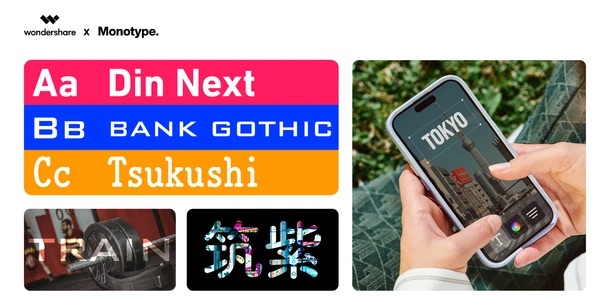
글로벌 폰트 및 서체 기술 기업 모노타입(Monotype)이 200종의 고품질 폰트를 원더쉐어(Wondershare)의 AI 기반 영상 편집 툴 ‘필모라(Filmora)’에 탑재했다고 밝혔다.
필모라는 전 세계 누적 4억 명 이상의 활성 사용자를 보유하고 있으며, 크리에이터, 교육 종사자, 기업 사용자들이 소셜 플랫폼, 교육, 마케팅 등을 위한 영상 콘텐츠 제작에 활용하고 있다. 이번 협업은 고품질 타이포그래피를 편집 환경에 직접 탑재함으로써 사용자가 툴을 전환하지 않고도 적합한 서체를 선택할 수 있도록 지원하며, 전반적인 제작 워크플로를 간소화한다.
이번 폰트 추가는 영상이 스토리텔링과 브랜드 구축의 핵심 형식으로 자리 잡으면서 온스크린 텍스트의 역할도 더욱 중요해지고 있는 상황에 발맞춰 진행됐다. 모노타입의 ‘Fonts, Feels, & Reels’ 연구에 따르면 응답자의 71%가 소셜 미디어 게시물을 만들 때 디자인 툴을 사용하는 이유로 ‘더 다양한 폰트를 쓸 수 있고, 세밀하게 조정할 수 있기 때문’이라고 답했다. 그만큼 폰트 선택과 디테일한 제어가 콘텐츠 완성도에 큰 영향을 미친다는 뜻이다.
또한 글로벌 사용자와 분산된 협업 환경이 늘어나면서 다양한 포맷과 디바이스, 언어에서 문제없이 사용할 수 있는 콘텐츠 자산의 중요성도 함께 커지고 있다. 필모라에 폰트를 직접 탑재함으로써 사용자는 폰트 선택과 적용을 보다 간편하게 처리할 수 있으며, 디자인 설정에 소요되는 시간을 줄이고 스토리텔링과 영상 제작 본연의 작업에 더욱 집중할 수 있다.
이번 폰트 추가로 필모라 사용자는 별도의 외부 툴을 거치지 않고 편집 화면 내에서 바로 모노타입 폰트를 선택·적용할 수 있다. 이를 통해 영상의 완성도를 높이는 동시에 작업 효율 또한 향상될 것으로 기대된다는 것이 모노타입 측의 설명이다.
필로마에 추가되는 서체들의 경우 필모라의 글로벌 크리에이터 커뮤니티 수요를 반영해 원더쉐어가 직접 선별했다. 강렬한 타이틀, 로어서드(lower-thirds), 자막, 온스크린 그래픽 등 다양한 영상 구성 요소에 적합하도록 구성됐으며, ‘DIN® Next’ ‘Tsukushi™’ 등 유명 폰트들도 포함한다. 또한 한국어를 포함해 번체 중국어, 일본어, 힌디어 등 글로벌 폰트를 지원해 다양한 언어 환경에서 활용할 수 있다.
유지 첸(Yujie Chen) 모노타입 APAC 총괄 부사장은 “AI 기반 툴의 확산으로 디자인 접근성이 크게 높아졌다”며 “경쟁이 치열한 콘텐츠 환경에서 타이포그래피는 차별화를 만드는 핵심 요소”라고 말했다. 이어 “원더쉐어와의 파트너십은 전 세계 크리에이터가 매끄러운 작업 환경과 높은 시각적 완성도를 바탕으로 아이디어를 구현하도록 지원하겠다는 공동의 의지를 보여준다”고 밝혔다.
크리스티 우(Christy Wu) 원더쉐어 필모라 제품 리드는 “전 세계 크리에이터가 배경과 언어, 기술 수준에 관계없이 아이디어를 명확하고 창의적으로 표현할 수 있도록 지원하는 것이 우리의 미션”이라며 “모노타입의 세계적 수준 타이포그래피를 필모라에 직접 탑재함으로써 전문적인 스토리텔링의 진입 장벽을 낮추고, 명확성과 일관성, 임팩트를 갖춘 커뮤니케이션을 가능하게 한다”고 말했다.